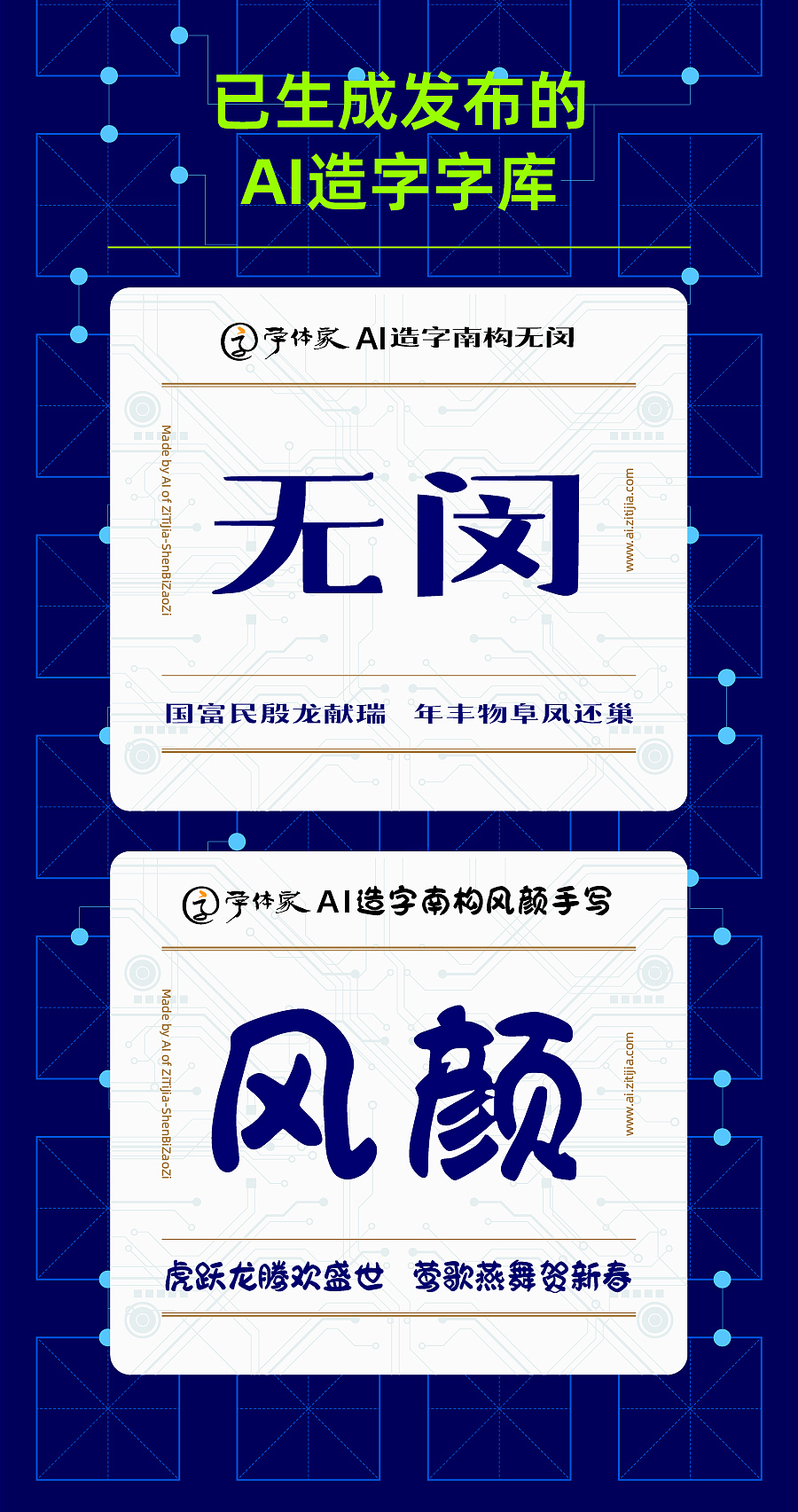
字体家AI造字,只要设计八个字就可造出一套6000+字库
什么是AI造字
近期,叶根友字体旗下字体家AI推出了一项革命性的“AI造字”服务,这标志着个性化字体创造领域的一大突破。借助先进的深度学习技术,用户只需手写八个汉字,字体家AI便能基于这些样本,生成一套包含6000多个汉字的个人专属字体库。
这一技术的实现得益于字体家AI搭载的一个参数规模高达1.5亿的神经网络模型。该模型可以精准捕捉并再现用户的书写风格,从而保留了每个人笔迹的独特性。字体家AI的这一服务不仅为用户提供了一种展现个性的新途径,同时也是传统书写艺术与现代科技结合的最新成果。
值得注意的是,字体家AI并非首家开发AI造字功能的企业。百度输入法和汉仪字库等已经推出了类似的服务。与这些服务相比,字体家AI更加注重用户体验和个性化输出。此外,阿里巴巴集团也通过AI造字技术,推出了阿里妈妈字体系列。
字体家AI的AI造字服务不仅支持屏幕手写输入,还允许用户上传纸质手写字迹的照片,这为追求更高设计精度的专业人士提供了便利。同时,字体家AI提供的字体售卖和API技术接入服务,为更广泛的应用场景提供了可能。
我们运用先进的人工智能技术,打造了一套具有学习字体风格特征的AI造字系统。仅需依据8个风格字,系统便能模仿出其他未见的中文汉字。然而,实验结果显示,10个风格字的效果更佳,因此我们推荐使用“纸上造字”。
AI系统如何学习字体风格?事实上,其中的细节我们无法完全知晓。在训练过程中,AI会以人类难以理解的方式,将字体风格映射到高维空间,并从高维空间的角度去思考字体的整体风格。
也就是说,AI并非以我们人类主观上的方式,通过“组合”、“拆解”笔画来实现字体生成。而是完全以“端到端”的形式,由AI自行思考、总结、推理出最终的生成结果。
这意味着:
我们无法完全理解AI的具体生成方式,因此目前无法要求我们对具体某个字、某个特定的笔画进行特定处理,一切都是AI自行思考的结果。
AI的效果与输入的图片密切相关,但我们实际上并不确定何种输入图能让其达到预期效果。目前来看,AI更擅长处理“干净”、“边界清晰”、“不带有过多纹理细节”的风格字。
由于是“端到端”的AI,错误率在所难免,只是多少的问题。我们需要正常看待这一现象,追求100%的完美是不现实的。可能同一个字,在某种字体上表现良好,在另一种字体上表现较差。因此,在使用AI工具时,请根据实际情况进行调整。我们亦无法保证生成的字均能达到完美效果。
然而,随着AI技术的不断发展,我们的技术也将逐步迭代,AI的完美程度必定会得到一定程度的提升。
字体家AI神笔造字系统如何学习字体风格?
我们运用先进的人工智能技术,打造了一套具有学习字体风格特征的AI造字系统。仅需依据8个风格字,系统便能模仿出其他未见的中文汉字。然而,实验结果显示,10个风格字的效果更佳,因此我们推荐使用“纸上造字”。
AI系统如何学习字体风格?事实上,其中的细节我们无法完全知晓。在训练过程中,AI会以人类难以理解的方式,将字体风格映射到高维空间,并从高维空间的角度去思考字体的整体风格。
也就是说,AI并非以我们人类主观上的方式,通过“组合”、“拆解”笔画来实现字体生成。而是完全以“端到端”的形式,由AI自行思考、总结、推理出最终的生成结果。
这意味着:
- 我们无法完全理解AI的具体生成方式,因此目前无法要求我们对具体某个字、某个特定的笔画进行特定处理,一切都是AI自行思考的结果。
- AI的效果与输入的图片密切相关,但我们实际上并不确定何种输入图能让其达到预期效果。目前来看,AI更擅长处理“干净”、“边界清晰”、“不带有过多纹理细节”的风格字。
- 由于是“端到端”的AI,错误率在所难免,只是多少的问题。我们需要正常看待这一现象,追求100%的完美是不现实的。可能同一个字,在某种字体上表现良好,在另一种字体上表现较差。因此,在使用AI工具时,请根据实际情况进行调整。我们亦无法保证生成的字均能达到完美效果。
然而,随着AI技术的不断发展,我们的技术也将逐步迭代,AI的完美程度必定会得到一定程度的提升。